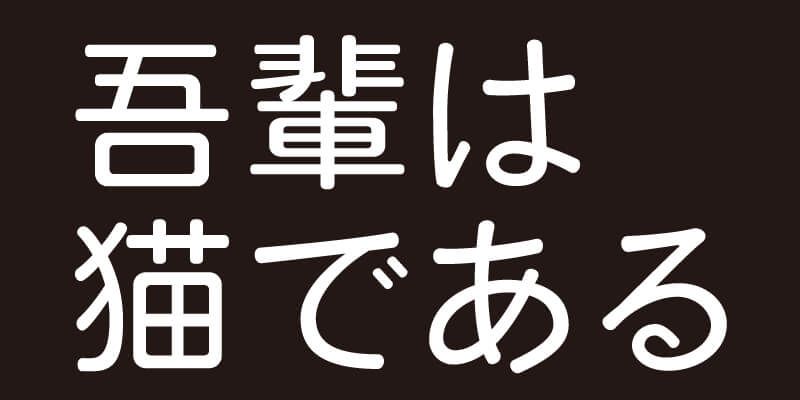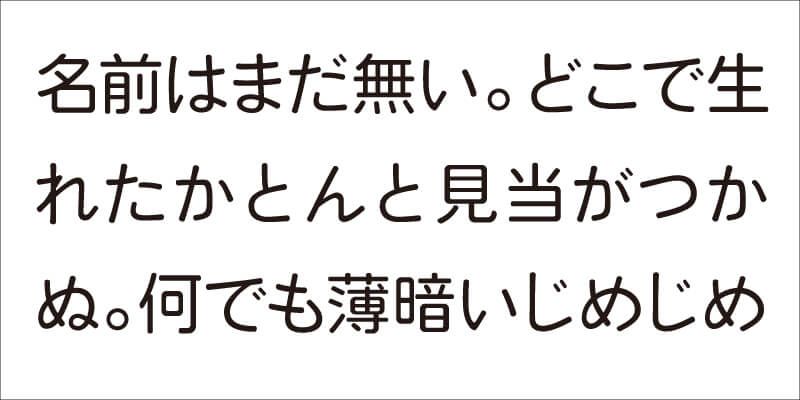
VDL-V7MaruGothic est une magnifique police gothique (sans empattement) arrondie et lisible, basée sur le design de VDL-V7Gothic. Avec cette police, vous ressentirez quelque chose de particulièrement éloigné des stéréotypes existants sur les conceptions de caractères « numériques ». VDL-V7MaruGothic possède des coins arrondis, ce qui amplifie la convivialité et la chaleur du design. Cette police offre une tension visuelle modérée avec une saveur nostalgique ; c’est le charme de VDL-V7MaruGothic.